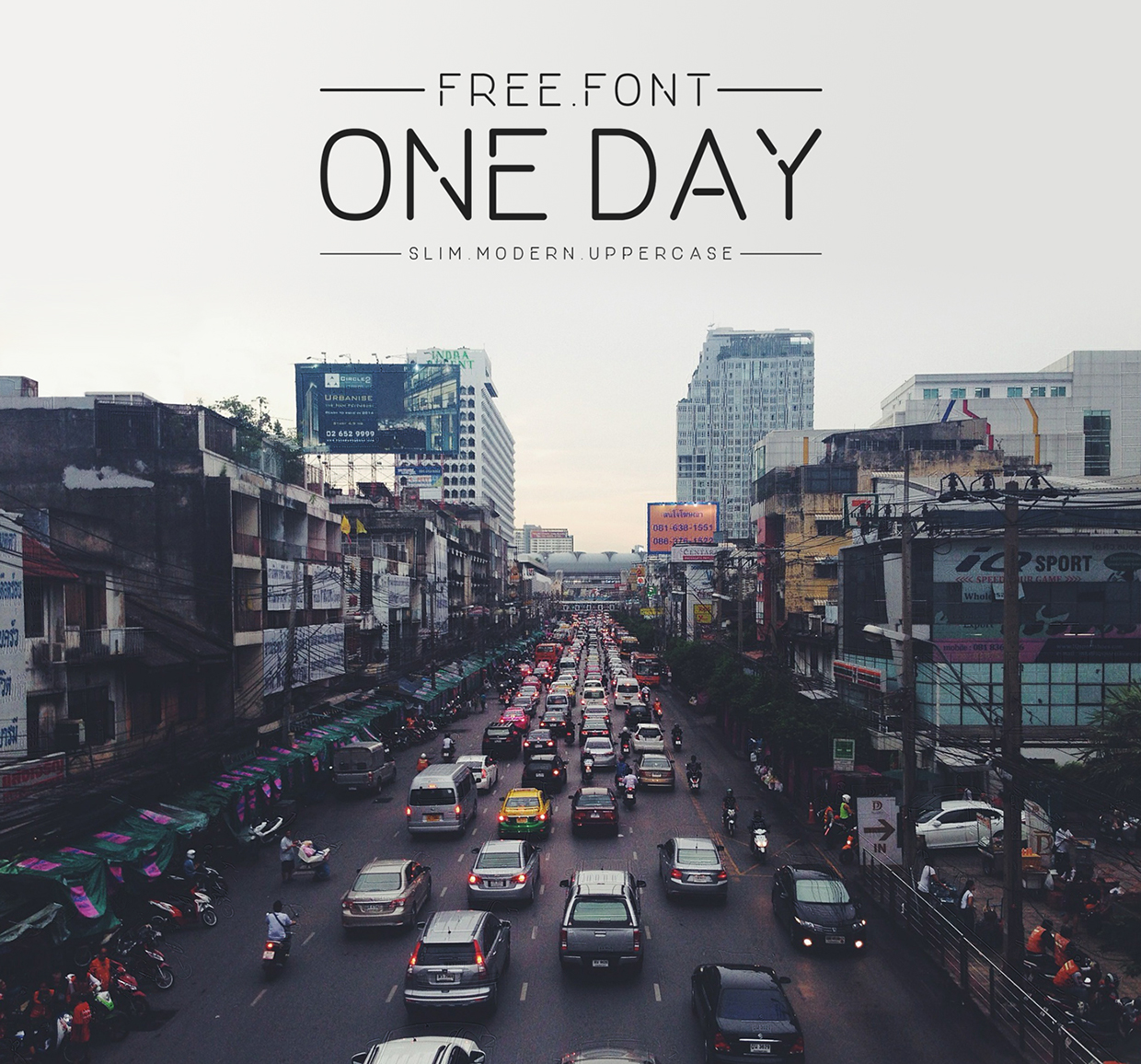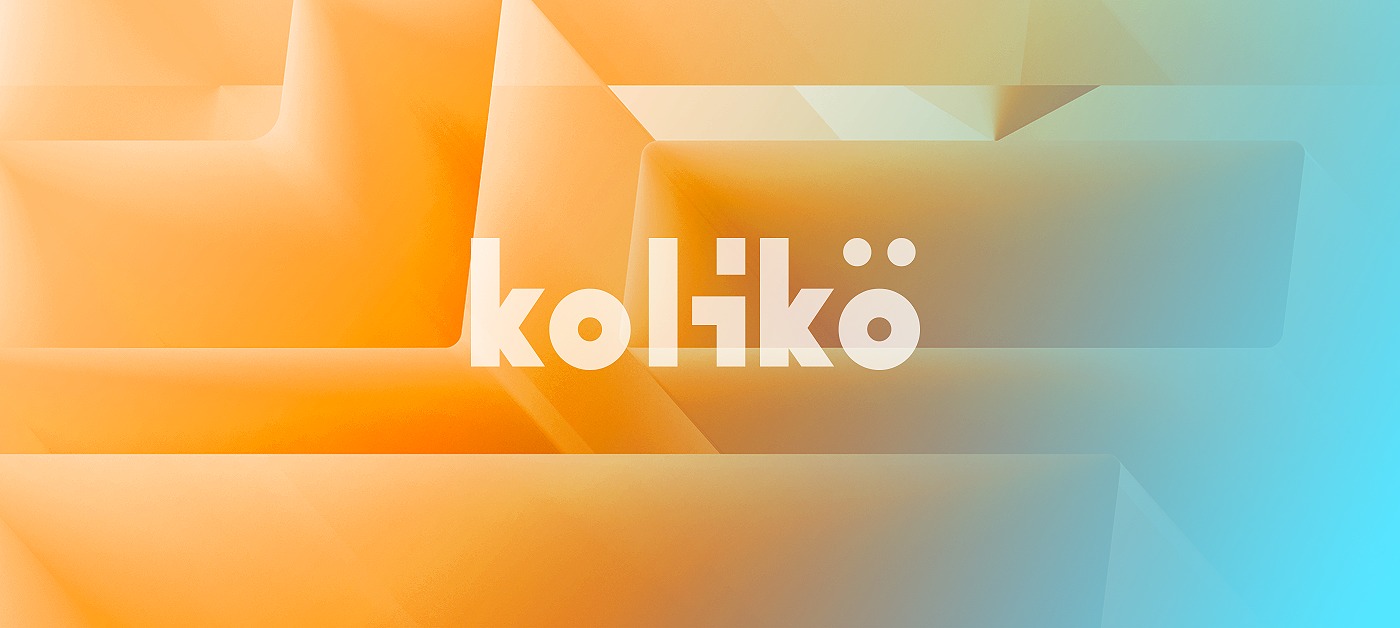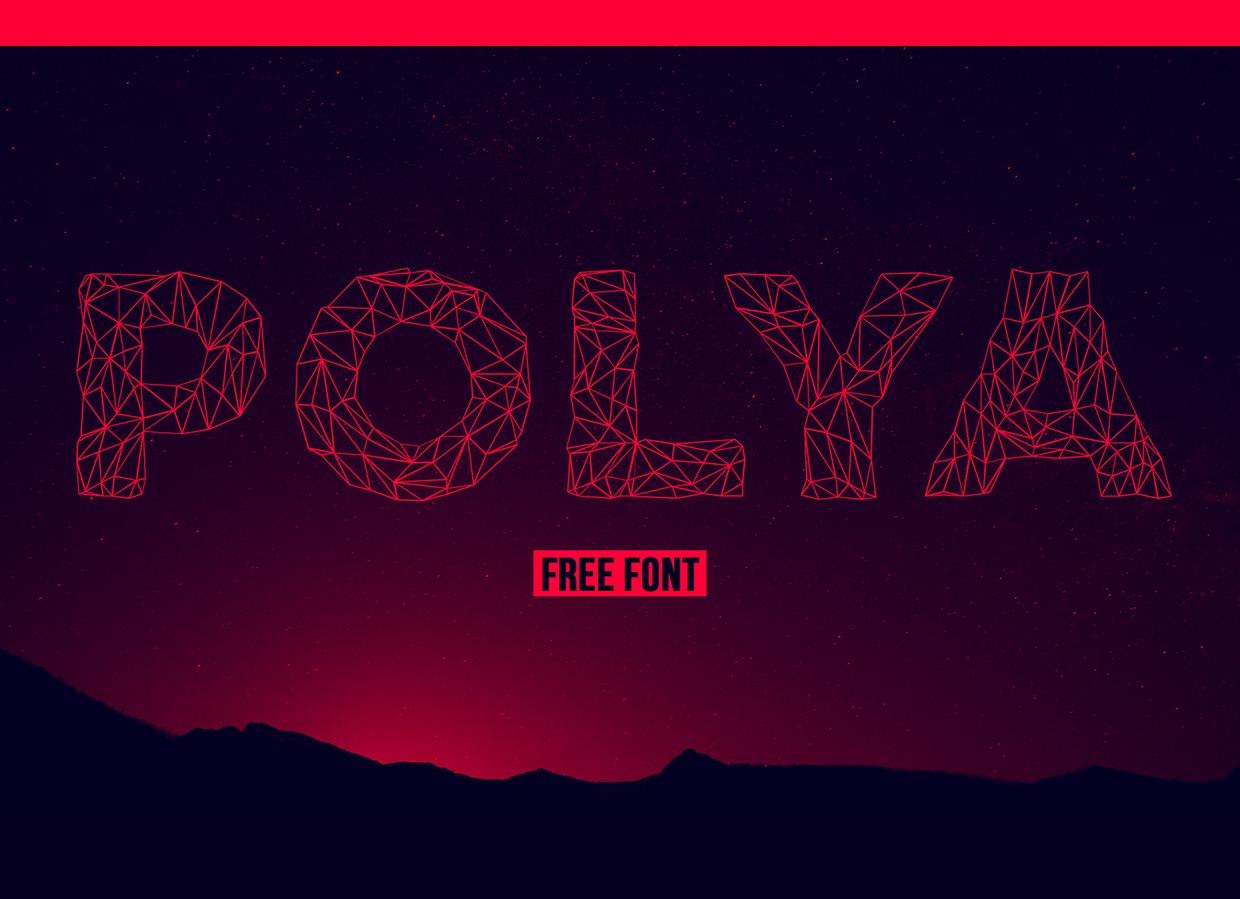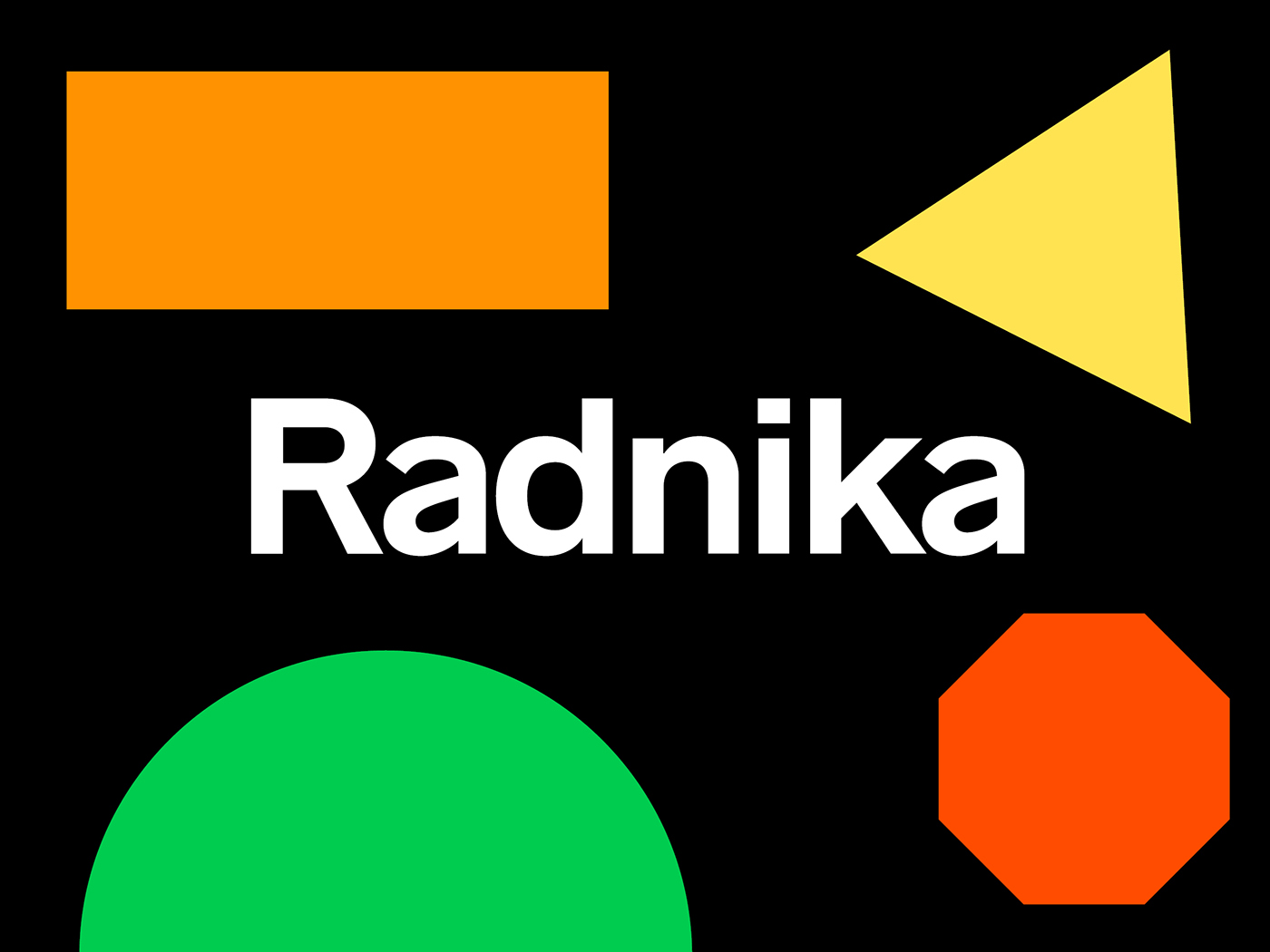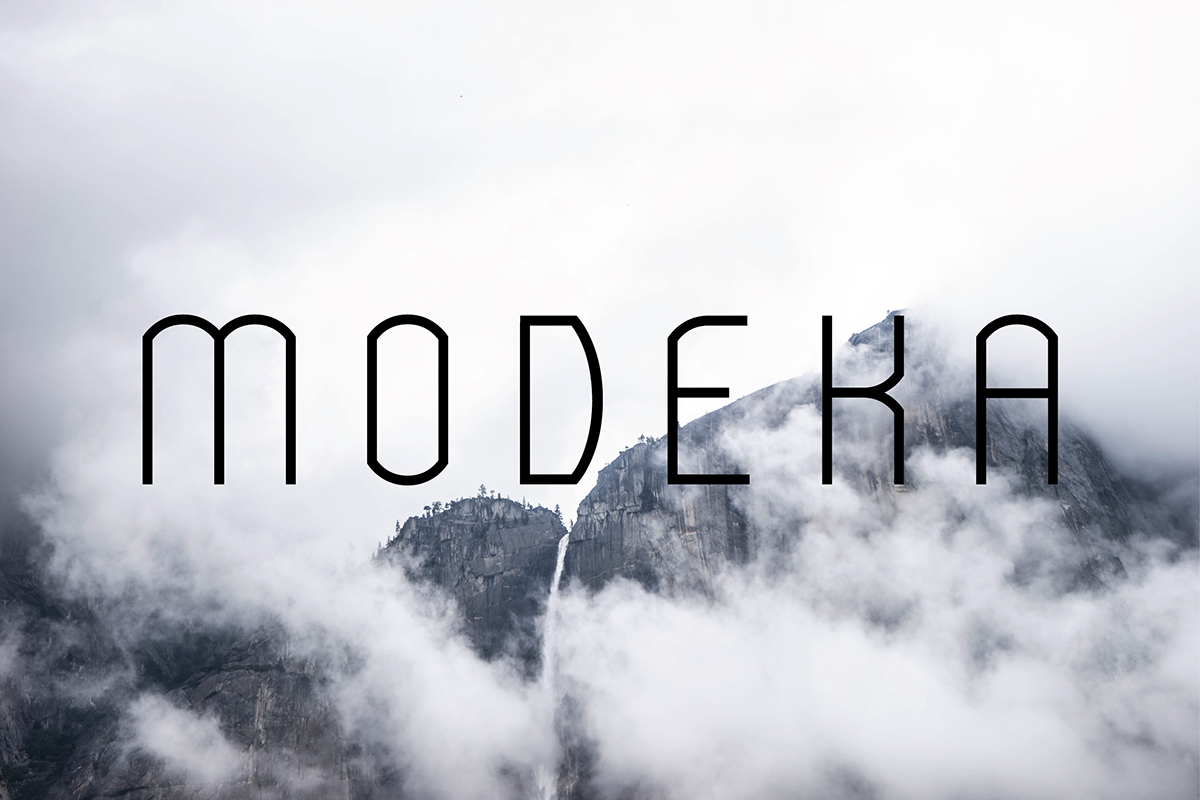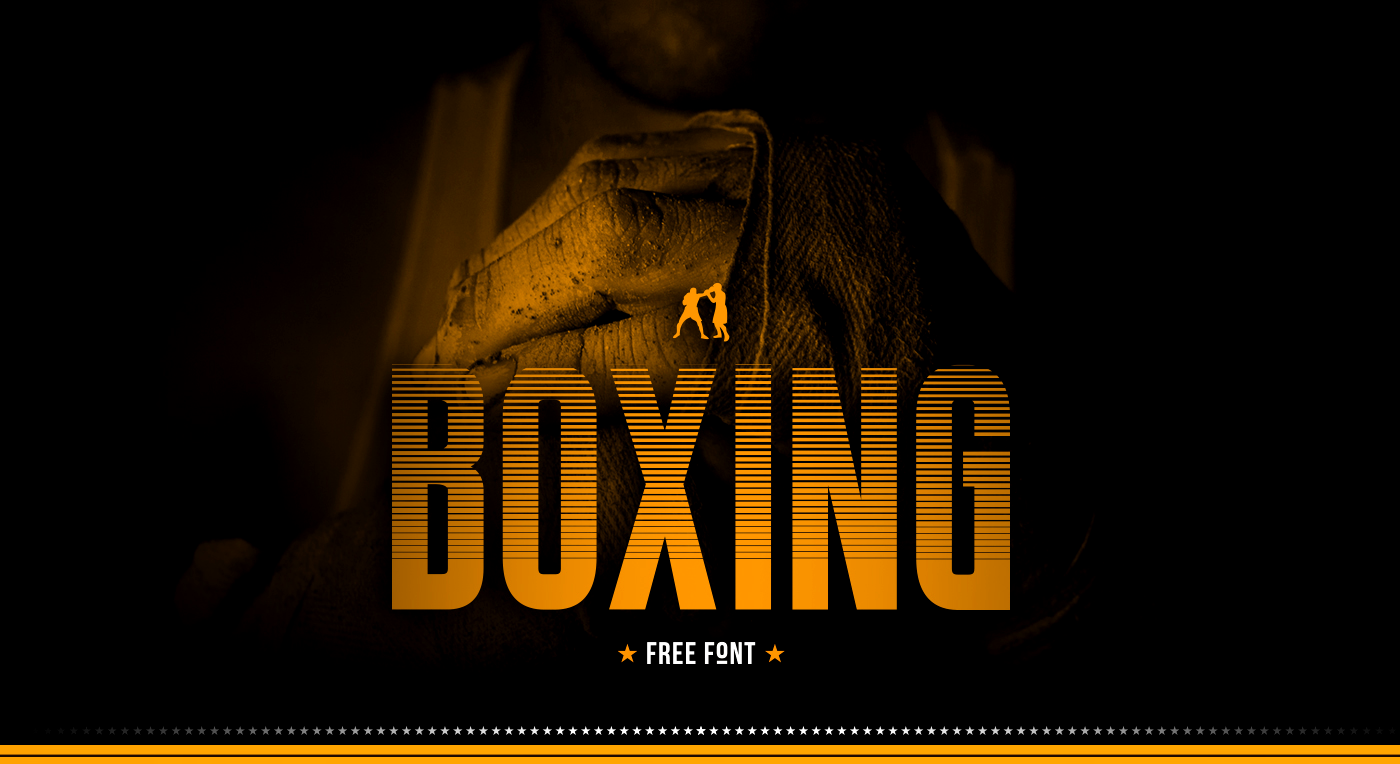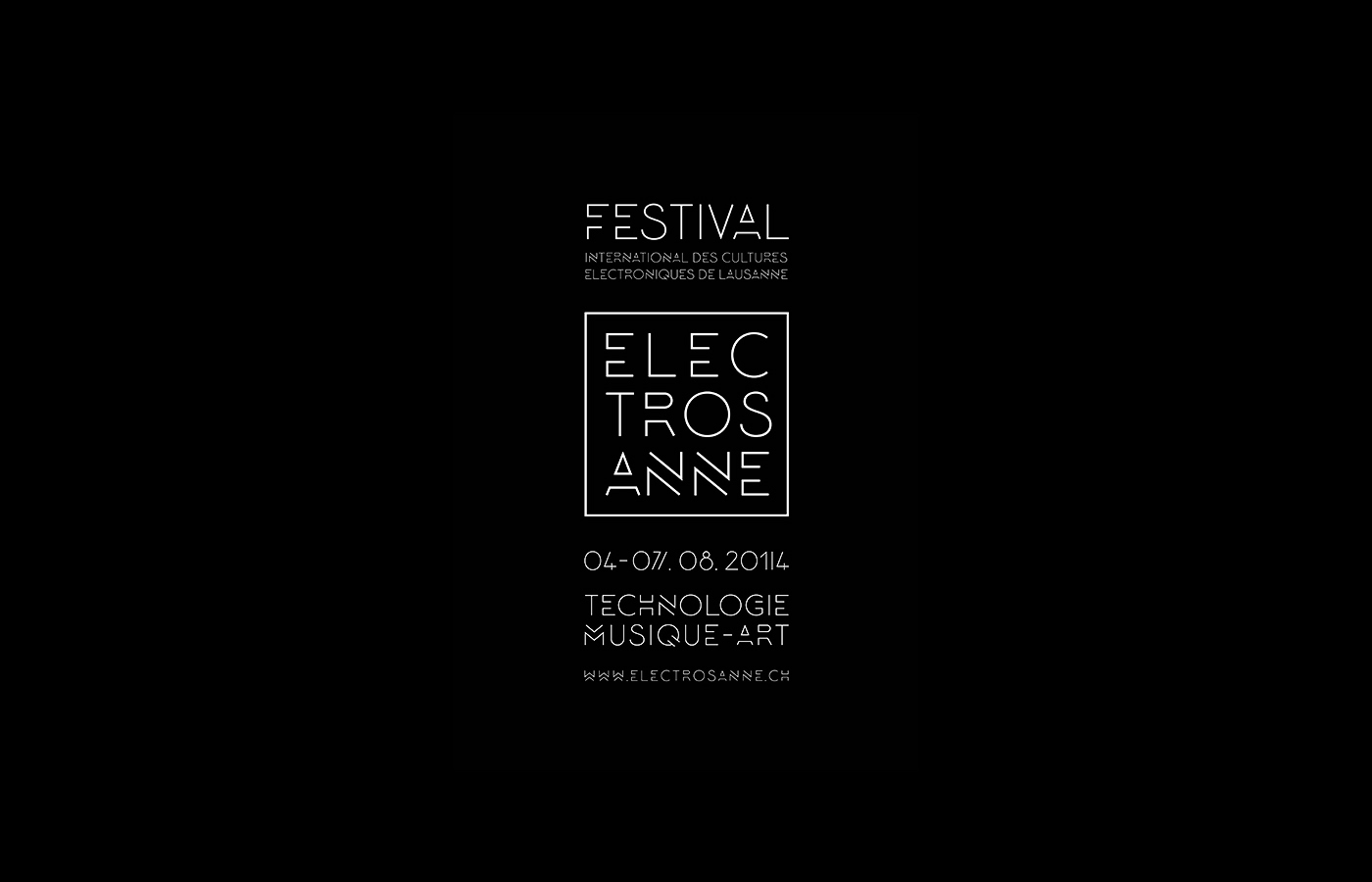
Hãy thử những font chữ này để định vị phong cách hiện đại cho thiết kế của bạn
Dựa trên những đường nét và hình dạng của hình học, các font chữ hiện đại mang lại cảm giác rõ ràng và dễ đọc. Cộng với những nét cách điệu sáng tạo bởi dấu gạch ngang hay dấu chấm sẽ mang lại cảm giác mới mẻ, hiện đại. Dưới đây là 50 font chữ sẽ mang thiết kế của bạn đến với thời đại mới. Tất cả những font chữ này đều được sử dụng miễn phí. Hãy cùng RGB lựa chọn một font chữ cho thiết kế của bạn nha.
[quote]1. LOMBOK[/quote]
By: Alexandre Pietre
[quote]2. AILERONS[/quote]
By: Adilson Gonzales de Oliveira Junior
[quote]3. ONE DAY[/quote]
By: Nawras Moneer.
[quote]4. Cooper Hewitt[/quote]
By: Chester Jenkins
[quote]5. AQUA[/quote]
By: Laura Pol
[quote]6.KOLIKö[/quote]
By: Fontfirma
[quote]7. POLYA[/quote]
By: Adrien Coquet
[quote]8. RADNIKA[/quote]
[quote]9. MODEKA[/quote]
By: Gatis Vilaks
[quote]10. HIGHER[/quote]
By: Marisa Passos
[quote]11.NORDIC[/quote]
By: Yana Bereziner
[quote]12.KOMODA[/quote]
By: Asia Ang
[quote]13. KOLLEKTIF[/quote]
By: Brave New Fonts
[quote]14.ACHI[quote]
By: Shibu PG
[quote]15. PARLEY[quote]
By: Filipe Rolim
[quote]16.AROMA[/quote]
By: Laura Pol
[quote]17. BOXING[/quote]
By: Tano Veron
[quote]18. MINIMALUST[/quote]
By: Pratama Yudha,
[quote]19.HYPED[/quote]
By: med ness
[quote]20. METRIA[/quote]
By: Jake Lunde